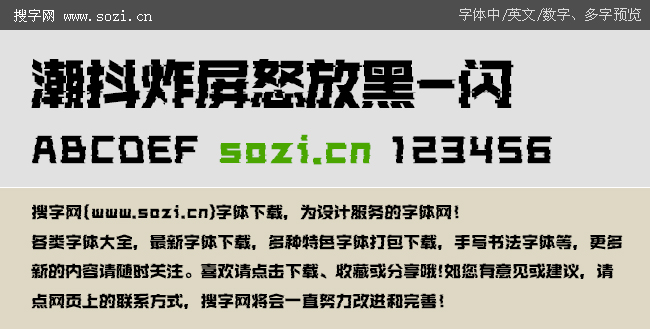
潮抖炸屏怒放黑-閃
搜字網(wǎng)提供一款潮抖炸屏怒放黑-閃中文字體下載,潮抖炸屏怒放黑-閃是一款藝術(shù)黑體字體,潮抖炸屏怒放黑以黑體字為基準(zhǔn),加入抖動(dòng)筆畫與切割錯(cuò)位效果,潮流動(dòng)感,重新定義時(shí)尚字體。適合用于標(biāo)題設(shè)計(jì)、海報(bào)設(shè)計(jì)、包裝設(shè)計(jì)等場(chǎng)景廣泛應(yīng)用。(本字體為個(gè)人非商用版,商用請(qǐng)聯(lián)系作者購(gòu)買授權(quán)。官方網(wǎng)址:http://www.reeji.com 聯(lián)系方式:021-58597892)